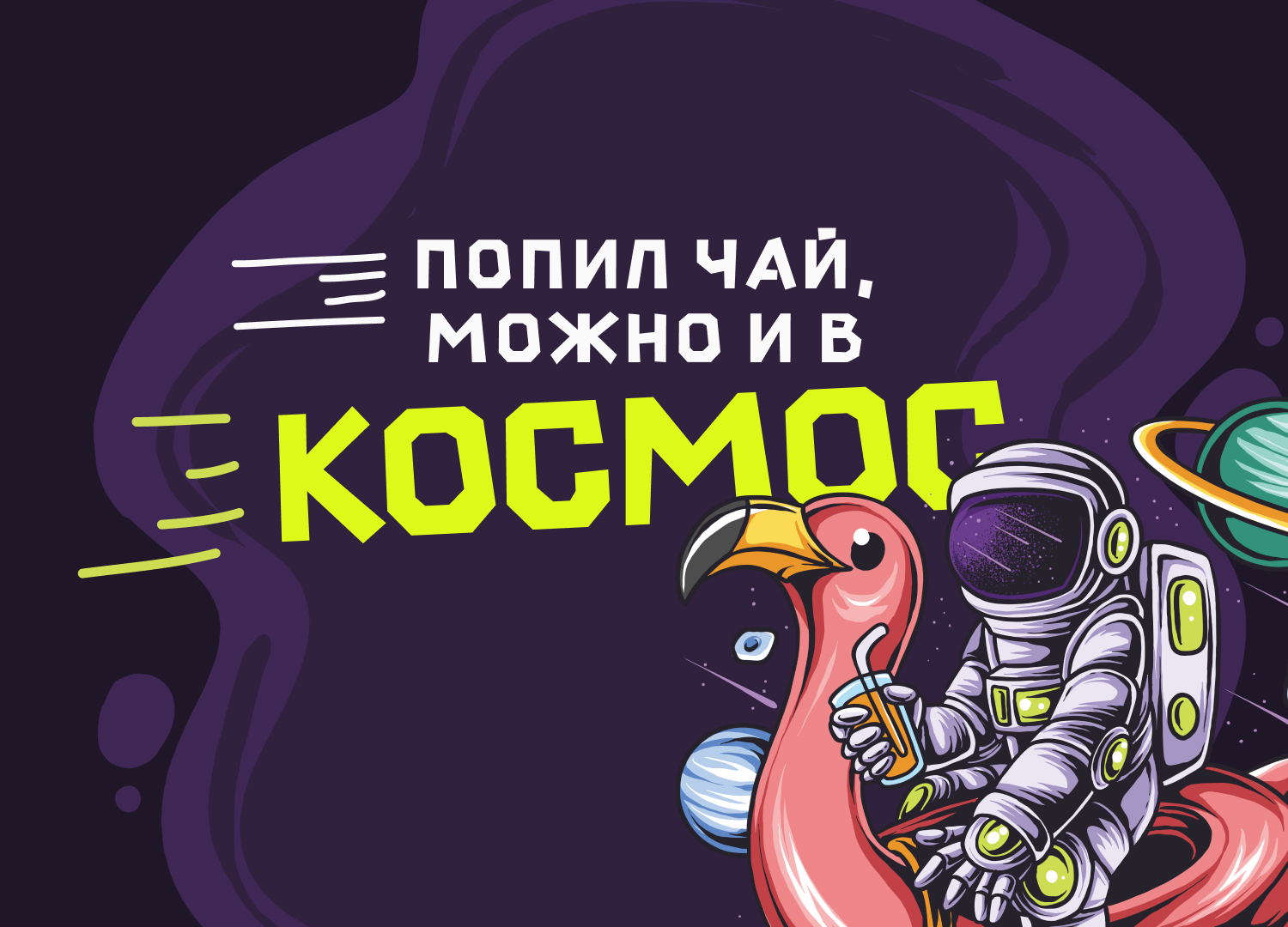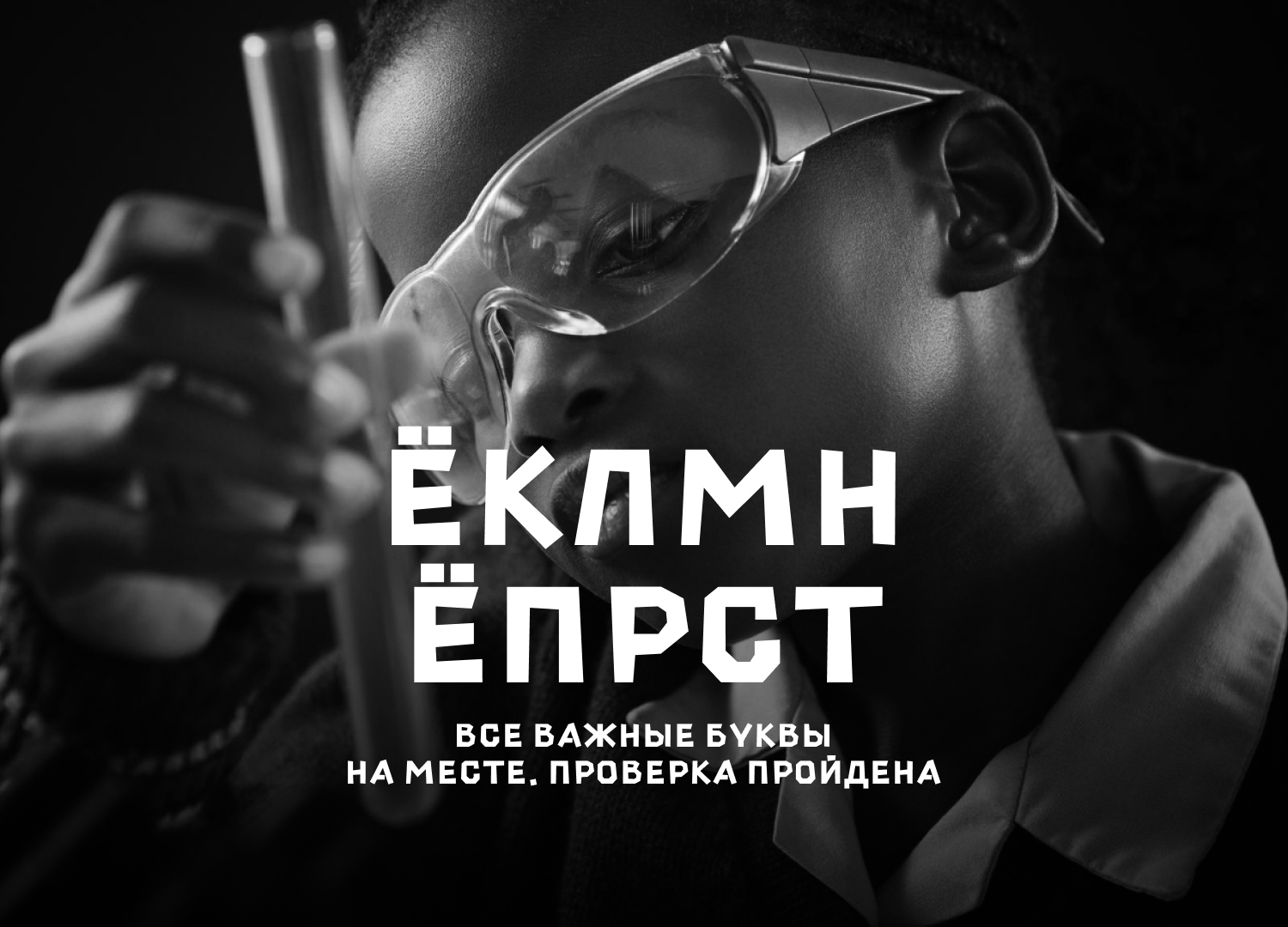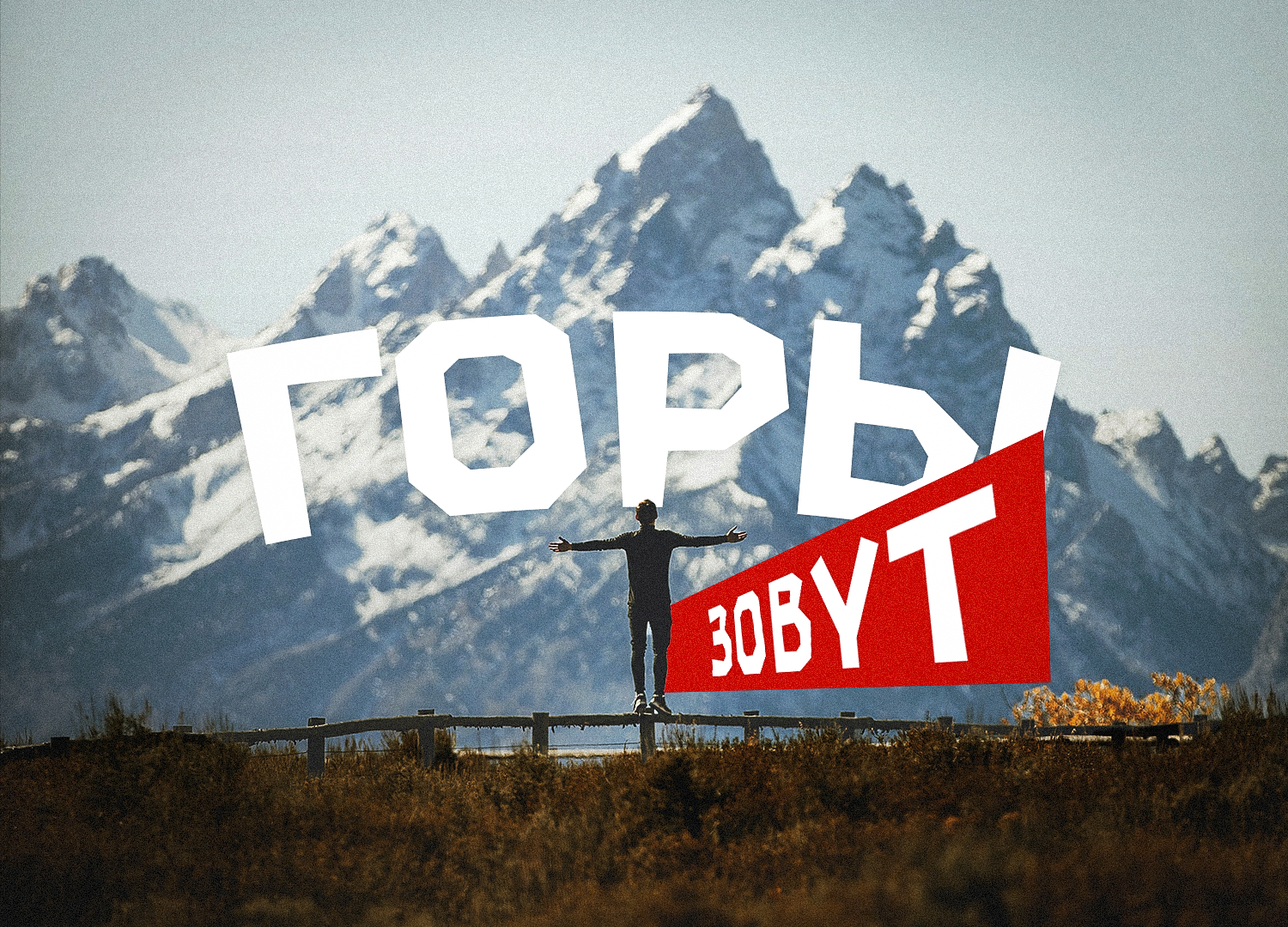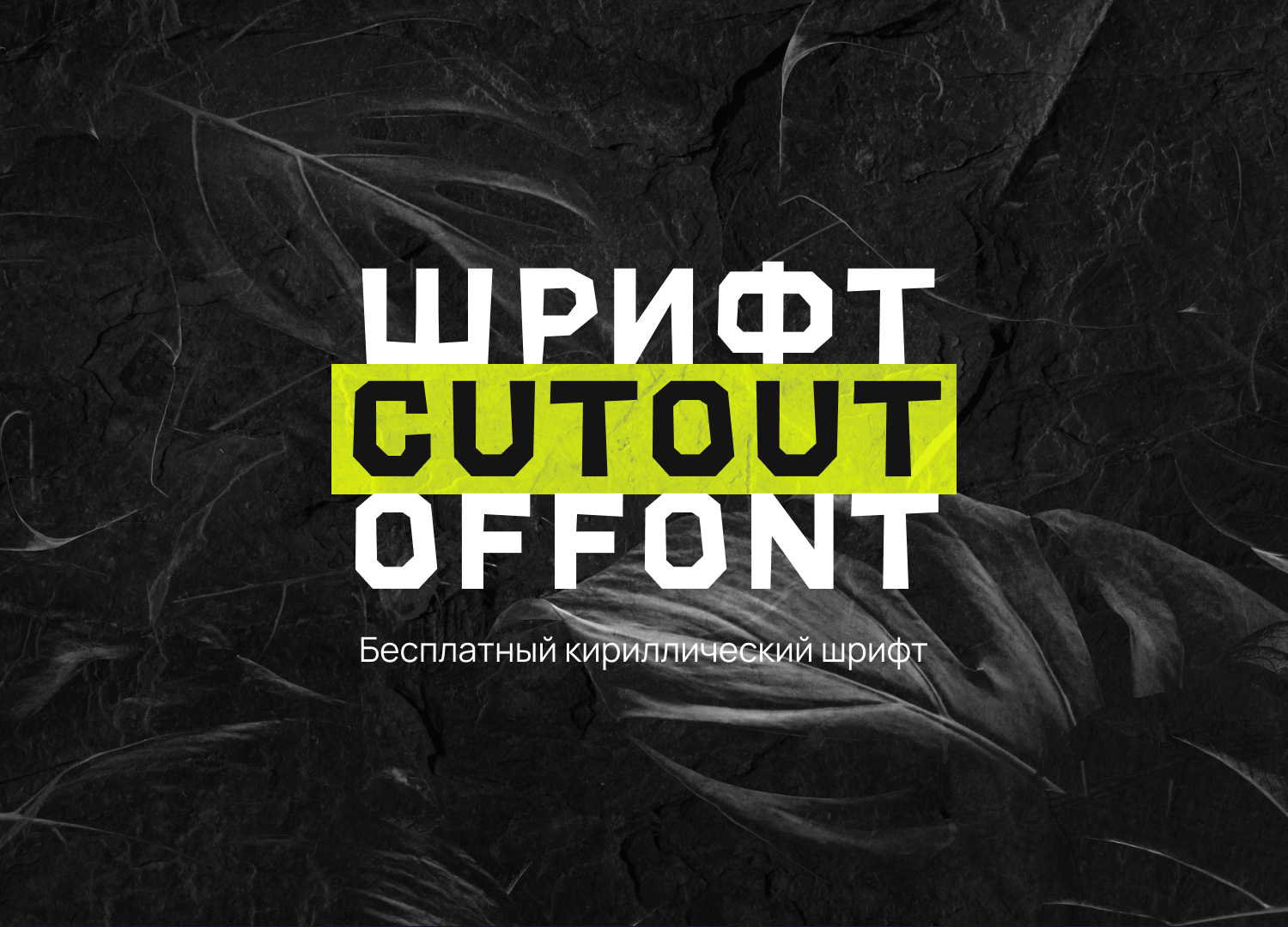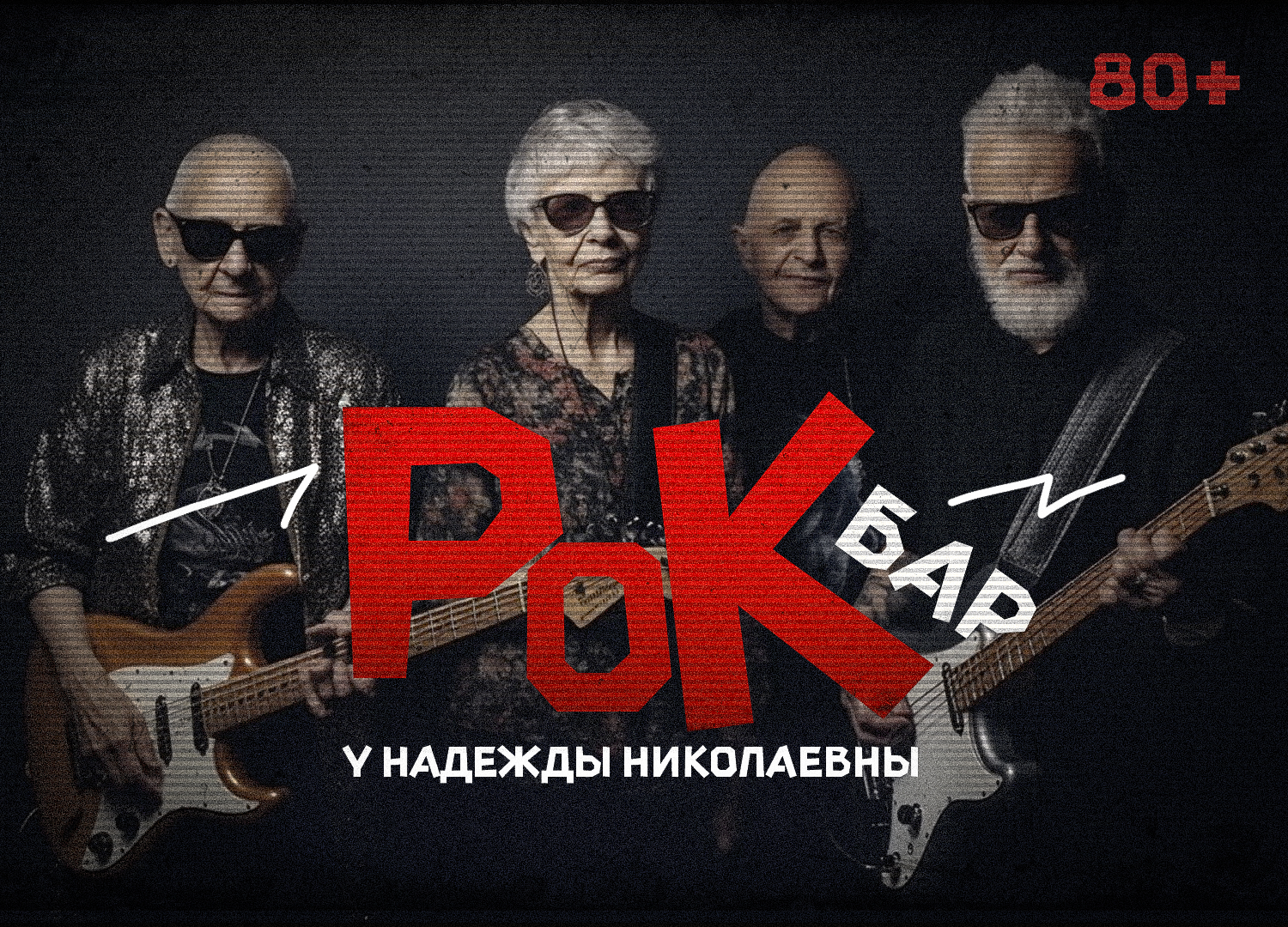
Бесплатный шрифт CutOutOFFont
Мощный, остроугольный шрифт. Подготовил короч еще одну презентацию) Прошу любить и жаловать.Автор — Serg Shishin Бесплатно для личного и коммерческого использования.